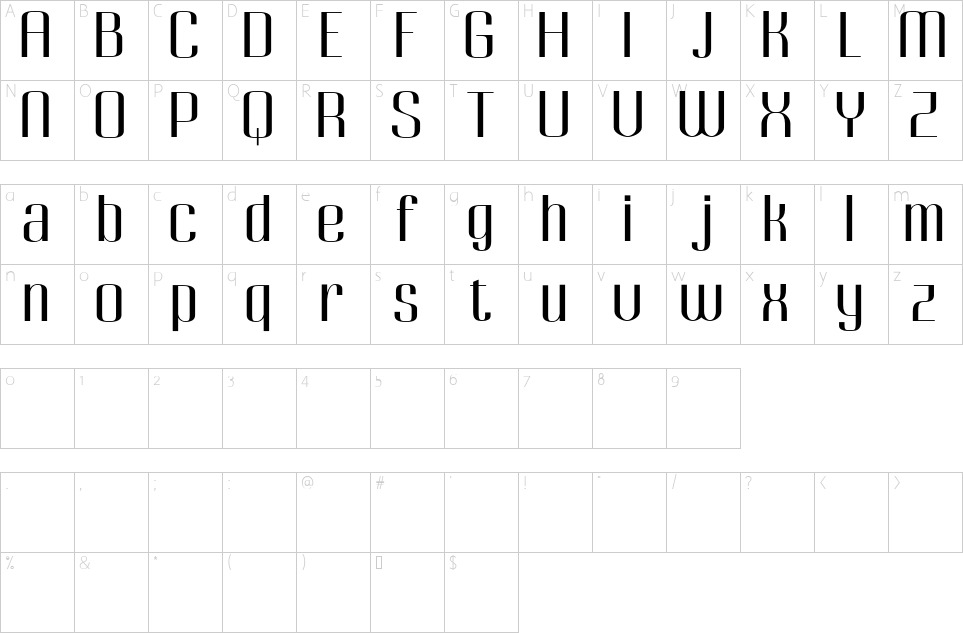
A Dazney é uma elegante fonte que se destaca por seu charme único e sua simplicidade, ideal para designers buscamar uma textura fresca em seus projetos digitais. Desenvolvida pela Craft Supply Co, a Dazney traz um toque suave e versátil que enriquece qualquer projeto gráfico, seja ele digital ou impresso. Com seu design minimalista e sua disposição uniforme, essa fonte se adapta perfeitamente às demandas de web e impressão modernas, oferecendo uma experiência de leitura fluida para os usuários. Recentemente, a Dazney já foi baixada 145 vezes, evidenciando o seu valor e popularidade entre designers de todo o mundo. O download da fonte Dazney está disponível tanto em Windows quanto Mac, permitindo que você escolha o caminho mais conveniente para adicionar um novo elemento ao seu design.